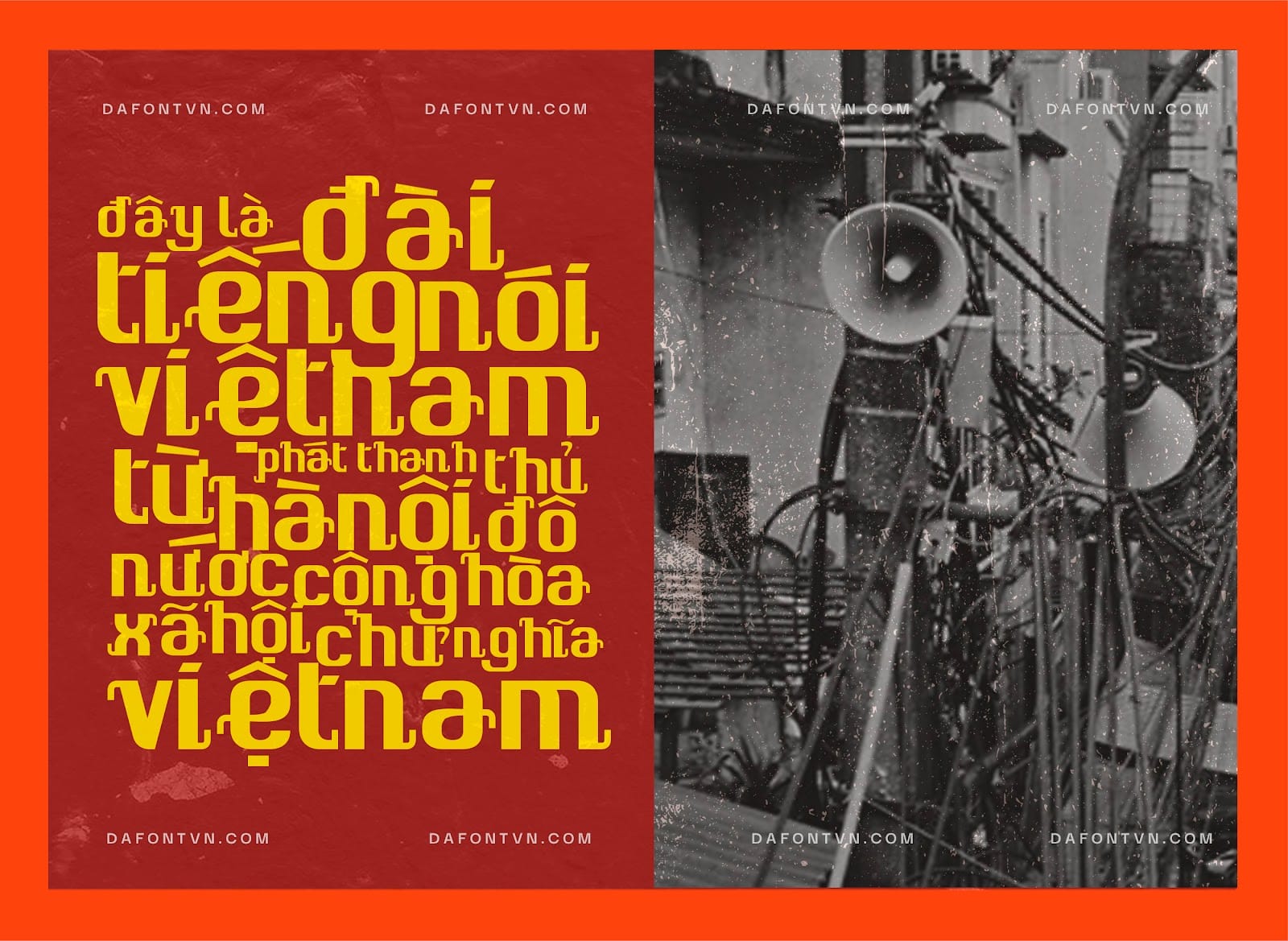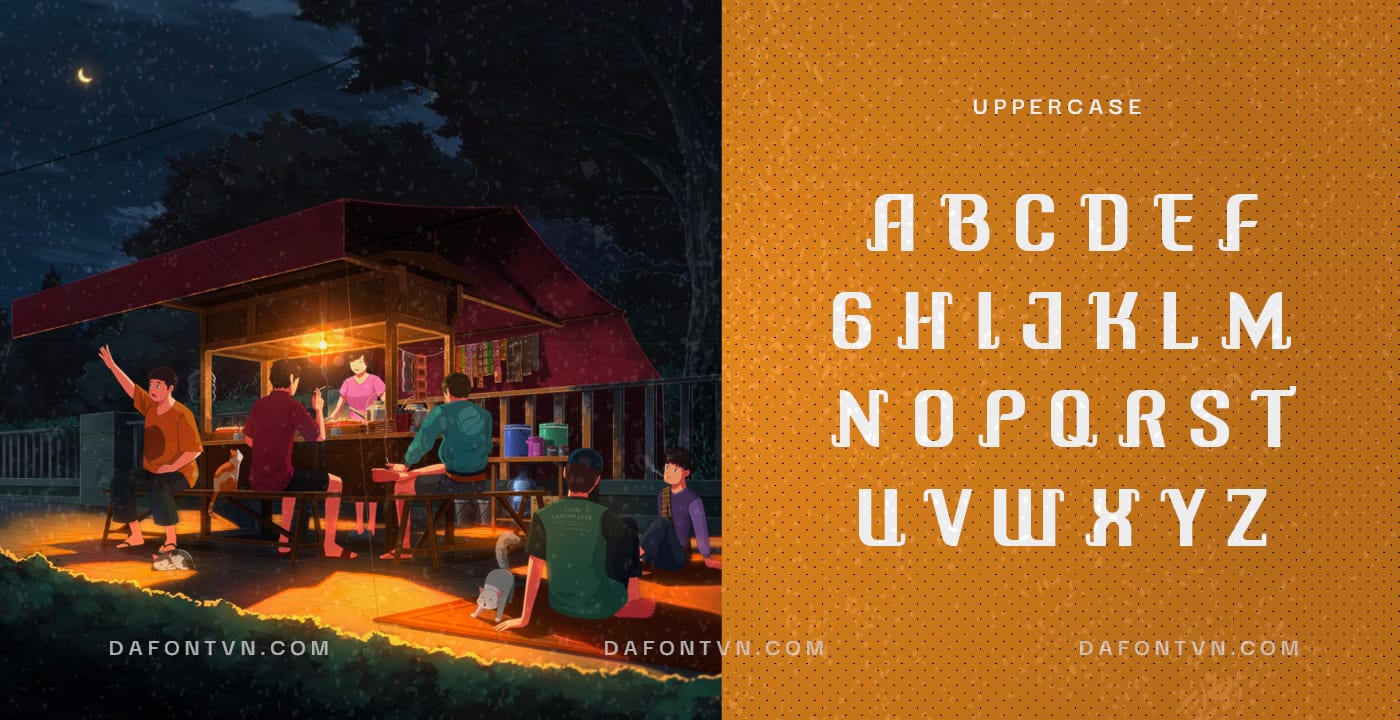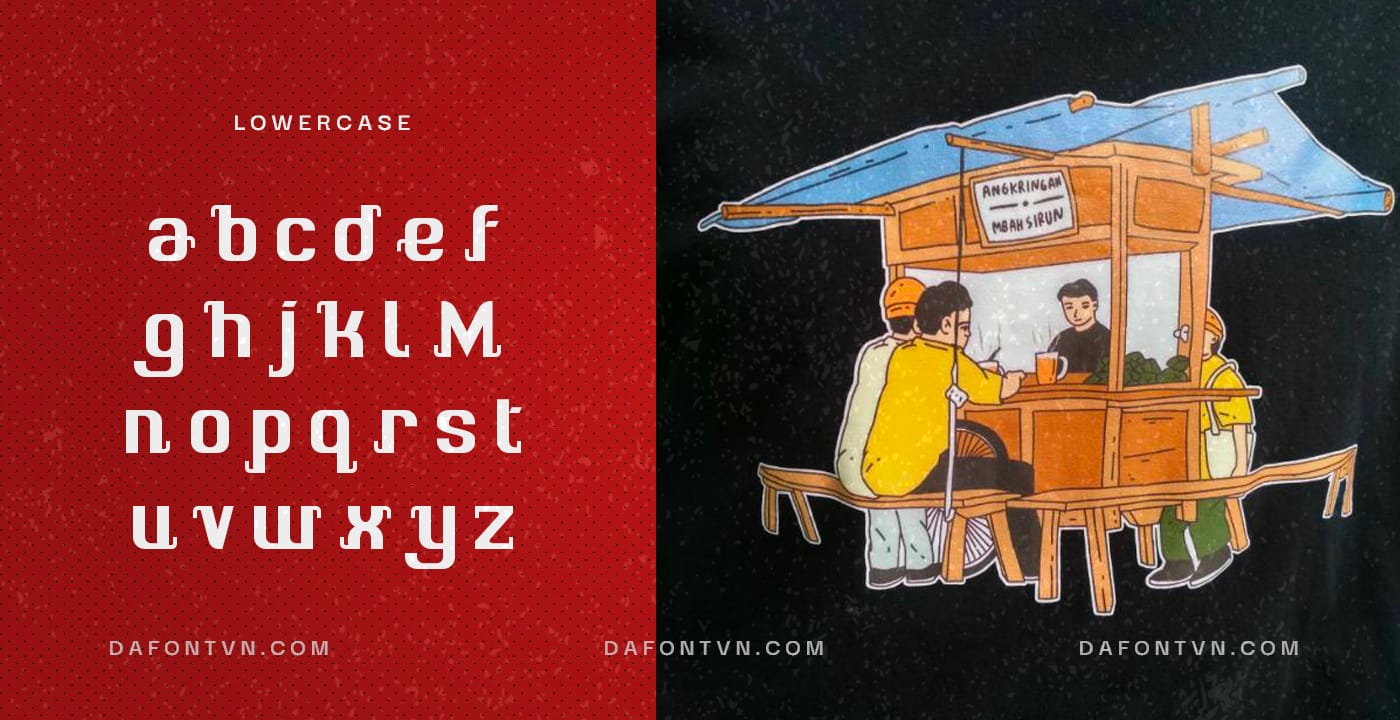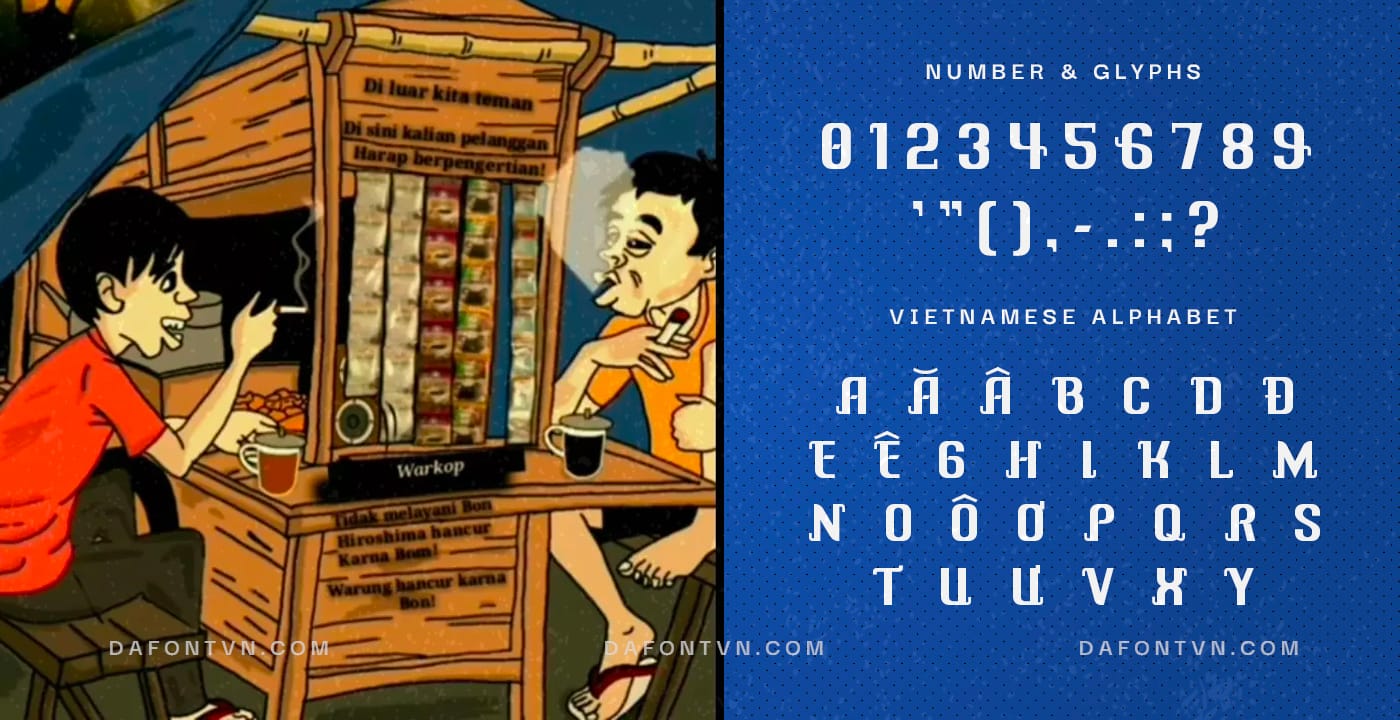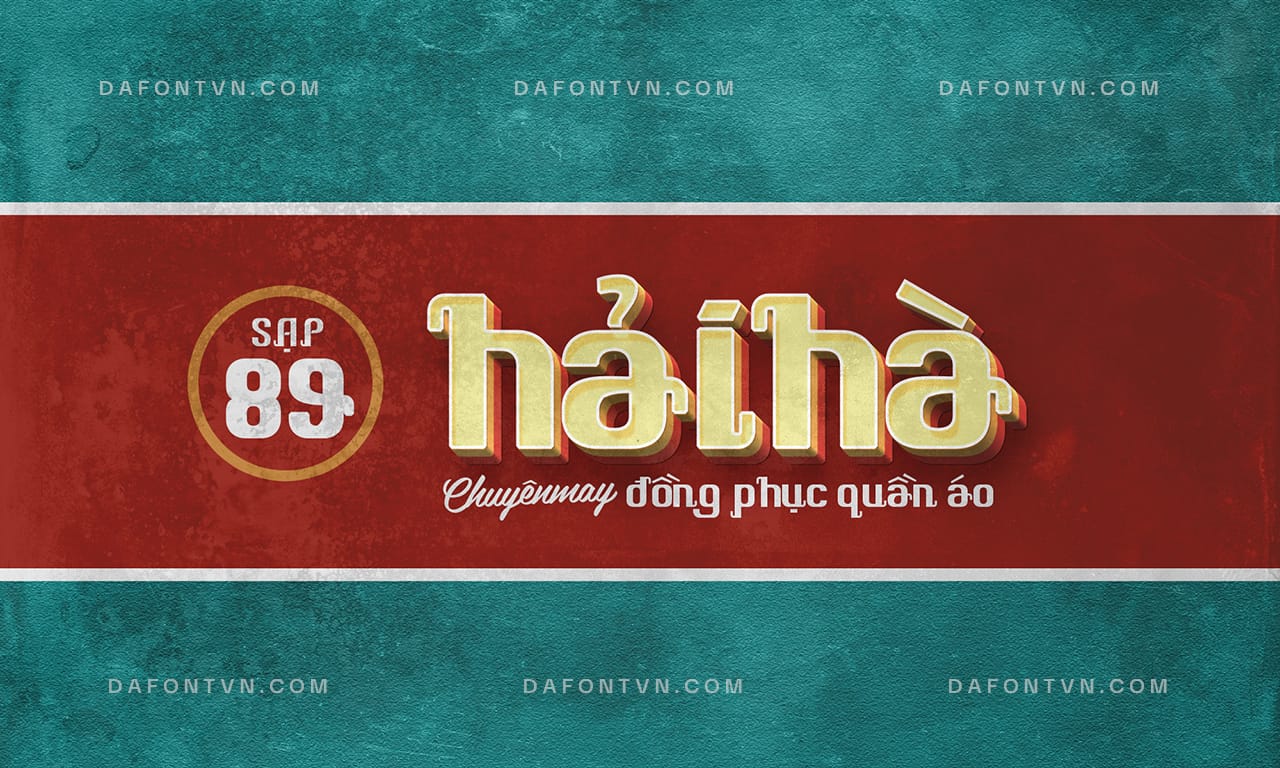
Angkring là kiểu chữ lấy cảm hứng từ Angkringan, đây là một trong những nền văn hóa & thực phẩm truyền thống ở Indonesia. Angkring có nghĩa là sự bình đẳng về địa vị xã hội đối với tất cả các tầng lớp trong cộng đồng. Các đường nét của chữ được thiết kế tượng trưng cho chiếc xe đẩy di động Angkringan.
Font mang phong cách cổ điển nhưng vẫn tối giản trên phông chữ này vì vậy phù hợp để áp dụng cho bất kỳ thiết kế nào.
Font được việt hóa bởi DafontVN với các dấu tiếng Việt mang phong cách xưa cũ, bạn có thể sử dụng font này cho các thiết kế retro như: cửa hiệu, tạp chí, biển quảng cáo,… Ngoài ra font được kerning, tối ưu để sử dụng dễ dàng trên bất kỳ phần mềm thiết kế nào.